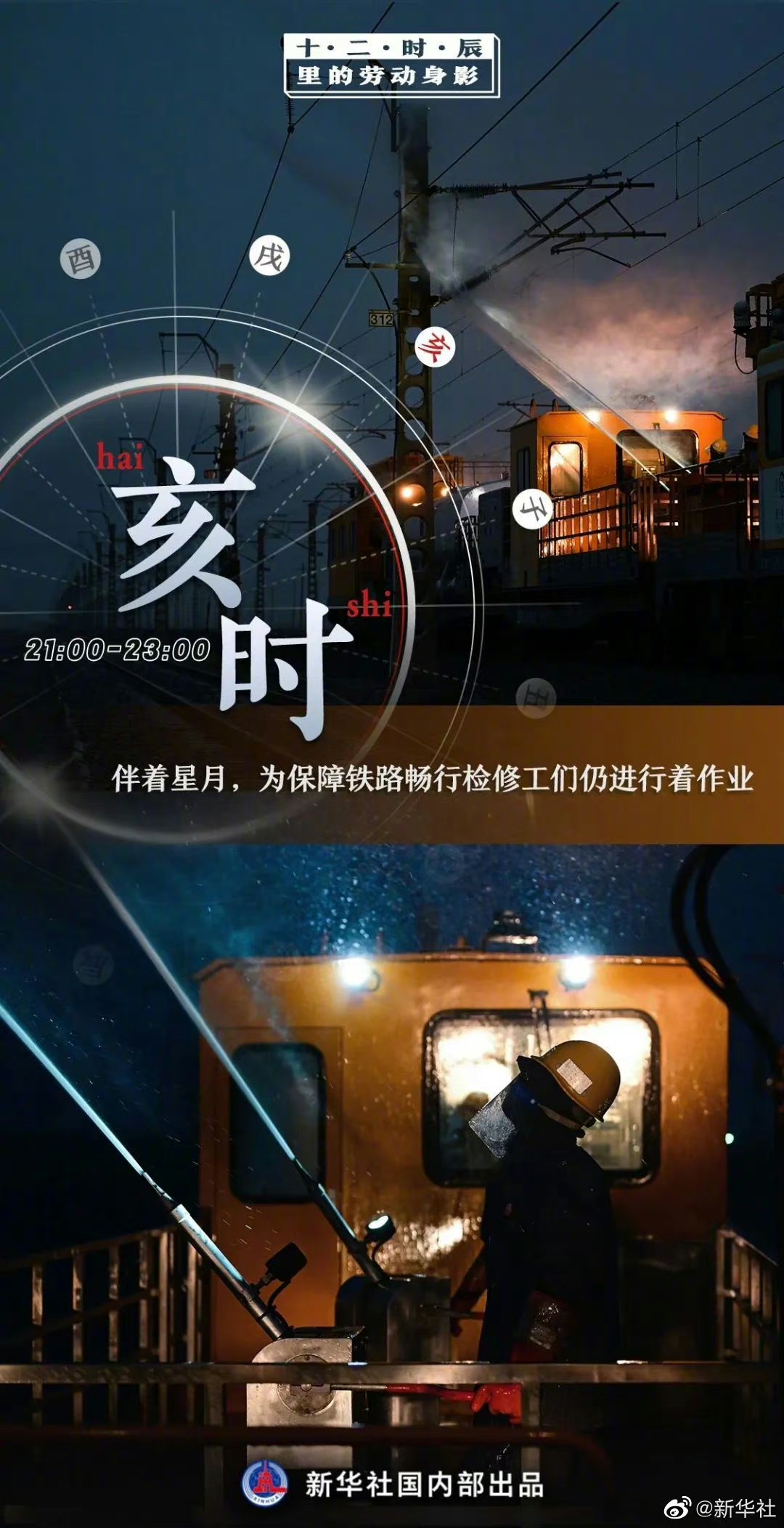
方正刘炳森隶书
刘炳森
隶书
刘炳森(1937-2005),当代书法家。曾任北京故宫博物院研究员、中国书法家协会副主席、中国文联副主席、中国佛教协会副会长、中国人民政治协商会议全国委员会常务委员。书法功力深厚,以隶、楷著称于世。其隶书充分展现了自己的创造性,形成了鲜明的个人风格,在当代书坛上独树一帜。
字体特征: 脱胎于铅字铜模字稿。这套字稿由刘炳森先生书写。风格沉稳大气,具有一种流畅自然、从容不迫的独特韵味。平正、敦厚、稳健、俊逸,符合现代审美情趣。